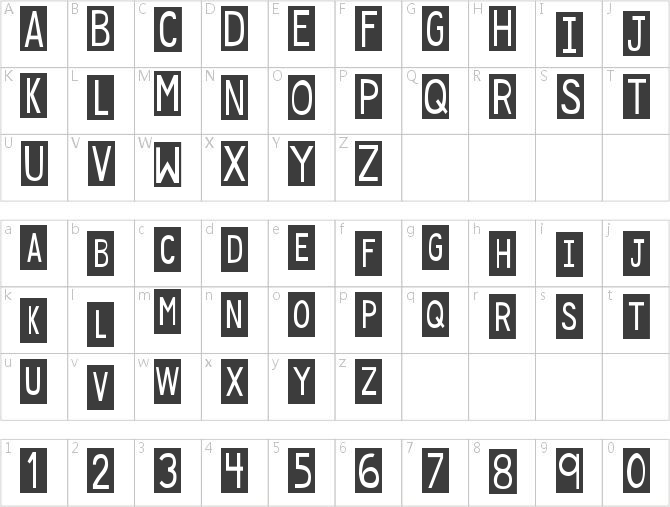
DJB Sticky Tape Labels Spaced 詳情頁
DJB Sticky Tape Labels Spaced
DJB Sticky Tape Labels Spaced介紹
DJB Sticky Tape Labels Spaced字體字庫是一款讓人賞心悅目、百看不厭的英文字體,適合各類廣告和產品包裝設計應用,字體大小0.01MB,格式為ttf字體,上傳用戶是釜源貿易,作者/版權方為未知